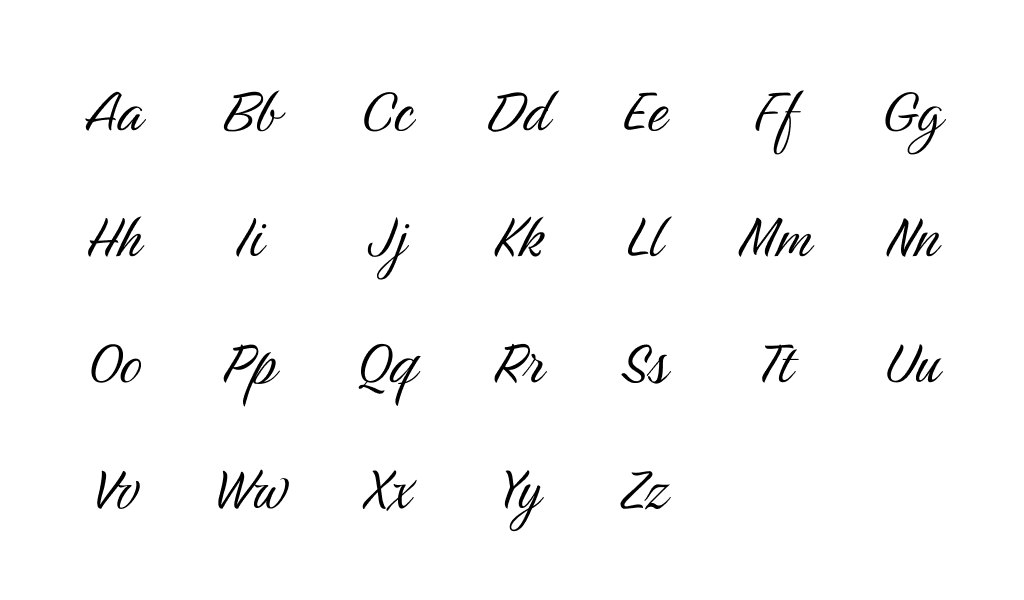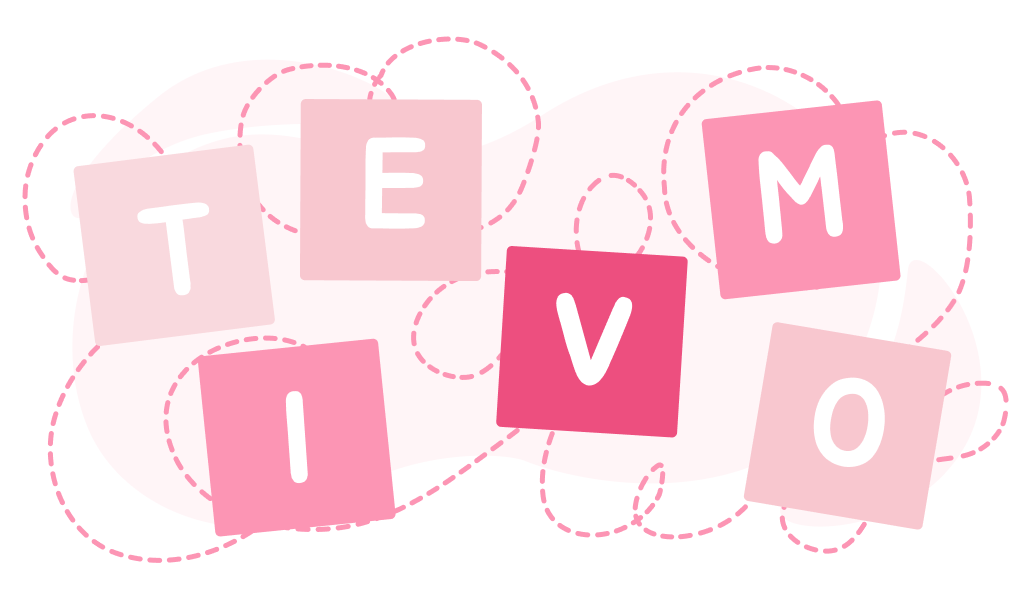
Typografie existiert seit Hunderten von Jahren in der Menschheit. Jeder von uns kommt täglich mit diesem Phänomen in Kontakt, indem er durch den Feed seines bevorzugten sozialen Netzwerks blättert, Kompositionen auf Produktetiketten im Geschäft liest und Werbetafeln betrachtet.
Typografie ist die visuelle Gestaltung von Texten, ein wichtiges Element des Brandings und eine Schlüsselkomponente der Komposition.
Typografie umfasst viele Aspekte: vom Layout von Zeitungen und Zeitschriften bis zur Entwicklung von Schriftarten für Logos. Mit der Entwicklung des technischen Fortschritts begann es sich überall zu verbreiten: Mittlerweile werden seine Methoden und Techniken nicht nur in Verlagen eingesetzt.
Die moderne Typografie ist nicht nur für die Lesbarkeit des Textes „verantwortlich“, sondern auch für dessen grafische Gestaltung.
Die Inschrift soll beim Leser bestimmte Assoziationen und Emotionen hervorrufen, zu konkreten Handlungen anregen.
Alle existierenden Schriftarten sind in vier Haupttypen unterteilt: Antiqua, Groteske, Handschrift und Display.
Antiqua (auch als „humanistischer Stil“ bekannt) ist eine Schriftart mit Serifen, kleinen Elementen, die über die Hauptbestandteile des Zeichens hinausgehen. Dies ist einer der ältesten und beliebtesten Stile und ist von der traditionellen Kalligraphie inspiriert.
Es wird angenommen, dass die Antiqua vor mehr als 600 Jahren erschien. Serifenschriften sind eine strenge, „formelle“ Option für formelle Dokumente. Sie finden sich häufig in Veröffentlichungen und gedruckten Dokumenten. Diese Schriftarten haben viele Ausführungsformen, sie können fett, kursiv usw. sein. Der bekannteste Serifenstil ist Times New Roman.
Die Groteske gewann erst vor relativ kurzer Zeit an Popularität – in der Mitte des 20. Jahrhunderts. Er unterscheidet sich vom oben erwähnten humanistischen Stil durch ein gotisches Aussehen. Die Schriftart gilt als moderner und klarer, gut geeignet für elektronische Texte – sie ist auf Bildschirmen gut lesbar. Diese Schriftart eignet sich hervorragend für Titel. Ihr bekanntester „Vertreter“ ist die Schriftart Arial.
Die handgeschriebene Schrift ist aufgrund ihrer Kunstfertigkeit und anmutigen Kurven einzigartig. Wie die Groteske erschien auch die handgeschriebene Schrift Mitte des 20. Jahrhunderts. Der Vorteil handgeschriebener Schriftarten ist Eleganz und Schönheit, der Nachteil ist, dass sie schwer lesbar sind: Nicht jeder kann sie schnell und einfach analysieren. Die Wahl solcher Stile sollte möglichst verantwortungsvoll angegangen werden: Die Schriftart soll anziehen, Interesse wecken und nicht durch ihre Komplexität abstoßen.
Die Displayschrift ist die ungewöhnlichste und informellste von allen. Die Schriftarten sind sehr originell, einprägsam und schaffen einen einzigartigen Stil. Diese Optionen eignen sich hervorragend für Überschriften und Logos.
Schriftarten stechen in einer eigenen Gruppe hervor – sie werden in Büchern und Online-Publikationen verwendet. Ihr Hauptvorteil besteht darin, dass sie auch in kleinen Größen verständlich sind.
Grundelemente der Typografie.
Wenn Sie die grundlegenden Komponenten kennen, können Sie sich besser in der Vielfalt der Stile zurechtfinden und schnell auswählen, was Sie benötigen.
Führend, führend – all dies sind Bezeichnungen desselben Konzepts – des Abstands zwischen Linien. Durch den richtigen Zeilenabstand wird der Text besser lesbar. Bei minimalem Zeilenabstand wird der Text unleserlich und extrem schwer lesbar. Auch ein zu großer Abstand erschwert die Wahrnehmung – man muss sich an die „goldene Mitte“ halten und einen Durchschnittswert wählen (zum Beispiel die Option „Standard“).
Der Buchstabenabstand oder Nachlauf ist der Abstand zwischen benachbarten Zeichen. Ein zu kleiner Abstand zwischen den Buchstaben führt zu einer Verkleinerung, ein zu großer Abstand macht es schwierig, ein Wort vom anderen zu trennen. Parameter können manuell eingestellt werden – moderne Programme bieten eine solche Möglichkeit.
Kerning regelt den Abstand zwischen Buchstaben nur innerhalb von Wörtern: Die Werte gelten nicht für den gesamten Text. Am häufigsten wird dieses Tool beim Zeichnen von Logos verwendet – es ermöglicht Ihnen, ungewöhnliche Stilideen umzusetzen.
Ein Graphem ist die kleinste Texteinheit: ein Symbol (Buchstabe, Zahl, Satzzeichen).
Eine Glyphe ist eine grafische Darstellung eines Graphems in einem bestimmten Stil.
Größe: Die Größe des Zeichens vertikal.
Lassen Sie uns separat ein paar Worte zu den Buchstaben sagen – Inschriften mit einzigartigen Stilen, die der Kalligrafie ähneln. Buchstaben sind nicht der Haupttyp für die Bildung von Schriftarten, werden aber häufig verwendet, um schöne Inschriften auf Bannern, Bannern usw. zu erstellen.
Die Typografie ist unglaublich umfangreich und spannend! Tauchen Sie ein in die Welt der Schriftarten und Schriftarten: Lernen Sie neue Stile und vergessen Sie nicht, mit Kombinationen zu experimentieren, denn nur so finden Sie eine Corporate Identity!